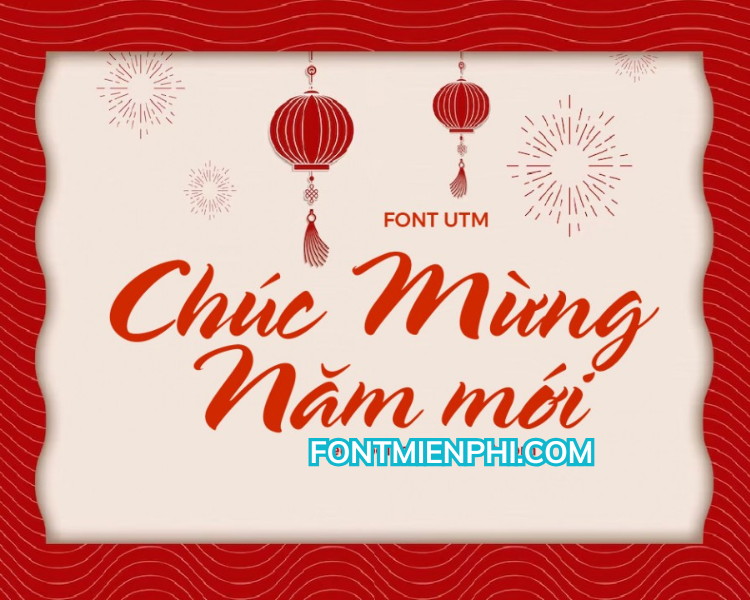
Việt hóa font UTM Spring ,font Tết
Việt hóa Font UTM Spring và Font Tết
Font UTM Spring:
• Là một trong những font chữ đẹp, phổ biến trong thiết kế đồ họa và in ấn tại Việt Nam.
• Thiết kế với kiểu chữ hiện đại, thân thiện, phù hợp cho nhiều mục đích sử dụng như bìa sách, poster, và các sản phẩm truyền thông khác.
• Việt hóa font này thường bao gồm việc bổ sung các ký tự tiếng Việt như ă, â, ê, ô, ơ, ư, và các dấu thanh.
Font Tết:
• Font chữ Tết được tạo ra để phù hợp với không khí lễ hội Tết Nguyên Đán.
• Thường mang đến cảm giác vui tươi, phấn khởi với các họa tiết và màu sắc đặc trưng.
• Việt hóa font này cũng cần đảm bảo rằng tất cả các ký tự tiếng Việt đều được thể hiện đầy đủ và rõ ràng.